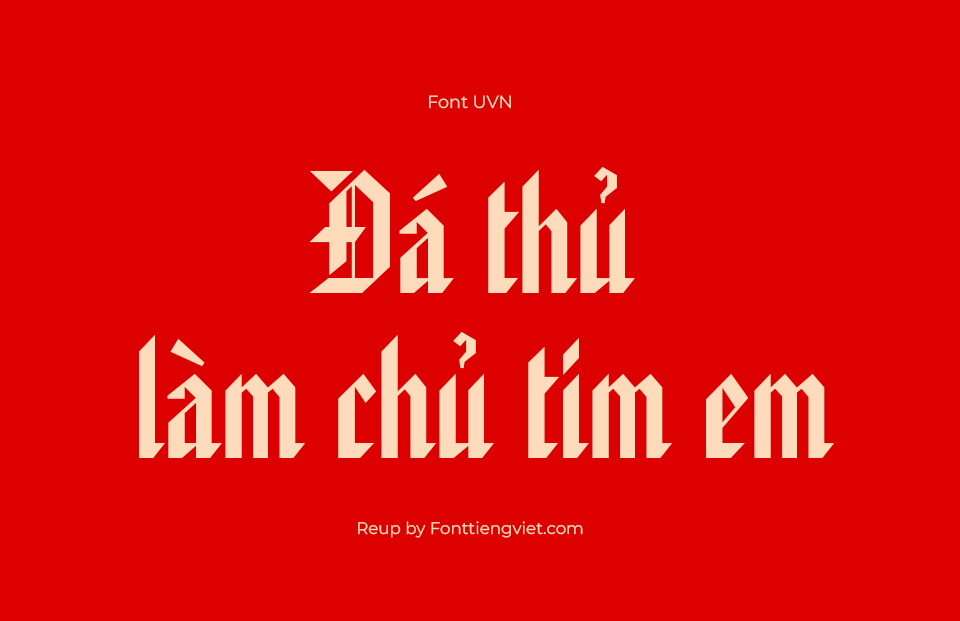
Font Việt Hóa UVN Hoa Ky
Giới thiệu về bộ Font Việt Hóa UVN Hoa Ky
Trong thế giới đồ họa hiện đại, việc tìm kiếm một bộ Font Miễn Phí chất lượng luôn là ưu tiên hàng đầu của các nhà thiết kế tại Việt Nam. Font Việt Hóa UVN Hoa Ky nổi lên như một lựa chọn hoàn hảo nhờ sự kết hợp giữa phong cách cổ điển và nét hiện đại tinh tế. Đây là một phần trong dự án UVN nổi tiếng, được tinh chỉnh kỹ lưỡng để hỗ trợ đầy đủ bảng mã tiếng Việt. Bộ chữ này không chỉ giải quyết triệt để lỗi hiển thị dấu mà còn mang lại vẻ đẹp thanh lịch, trang trọng cho mọi văn bản. Với đường nét rõ ràng, kiểu dáng vững chãi, nó giúp người dùng dễ dàng truyền tải thông điệp một cách ấn tượng nhất trên các phương tiện truyền thông số.
Ưu điểm nổi bật của Font Việt Hóa UVN Hoa Ky
Thiết kế tối ưu cho học tập và công việc
Đặc điểm nổi bật nhất của Font Việt Hóa UVN Hoa Ky chính là khả năng đọc hiểu cực cao. Đối với môi trường học đường, các thầy cô giáo thường xuyên sử dụng bộ font này để soạn thảo giáo án hoặc thiết kế bằng khen vì sự chỉn chu và nghiêm túc. Cấu trúc chữ được thiết kế cân đối, khoảng cách giữa các ký tự được tính toán khoa học, giúp người xem không bị mỏi mắt khi đọc các đoạn văn bản dài trên màn hình máy tính.
Khả năng ứng dụng linh hoạt trong đa dạng lĩnh vực
Không chỉ giới hạn trong văn bản hành chính, Font Việt Hóa UVN Hoa Ky còn được ứng dụng rộng rãi trong thiết kế banner, thiệp mời và tiêu đề sách. Khả năng tương thích tuyệt vời trên các phần mềm đồ họa như Photoshop hay Illustrator giúp quy trình sáng tạo trở nên mượt mà. Bạn có thể dễ dàng cài đặt bộ font này trên cả Windows và macOS để phục vụ nhu cầu cá nhân.
Kết luận và cách sở hữu bộ font chất lượng